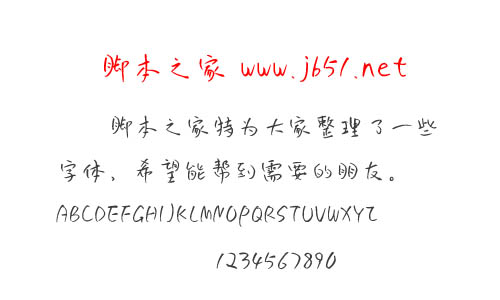
田相岳圓楷體字體是一款全新推出的手寫藝術(shù)設(shè)計的字體,該字體是圓體和楷體的首度交融,以黑體為楷體而設(shè)計,線條粗細適中,整體效果非常的出色,能夠適用于大標題、品牌廣告宣傳等需要強力視覺表現(xiàn)的環(huán)境,同時也可用于藝術(shù)設(shè)計、包裝印刷、簽名設(shè)計、圖形設(shè)計等領(lǐng)域,歡迎有喜歡或需要此字體的朋友們前來下載使用。